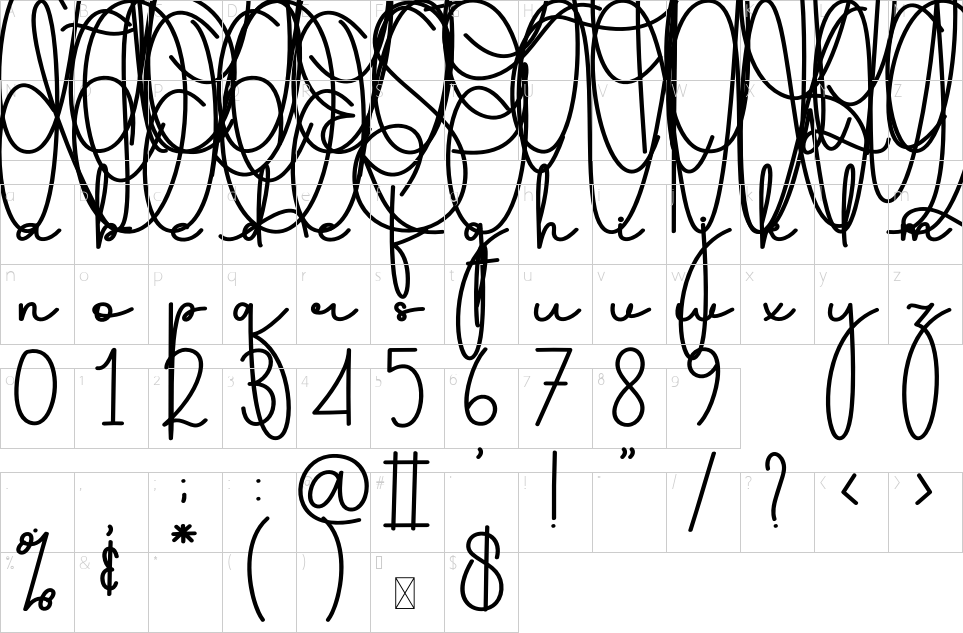
Descubra Mountain font, uma elegante fonte gráfica disponível gratuitamente para Windows e Mac. Desenvolvida por William Jhordy, Mountain font já foi baixada 343 vezes. Essa fonte adquirem um toque natural e amigável, perfeita para uso em design de sites, materiais de marketing e até mesmo em criações digitais pessoais. Se você está procurando por uma fonte que traga um pouco de natureza ao seu trabalho, Mountain font é uma escolha sólida e versátil. Não hesite em explorá-la, é um recurso gráfico que pode muito.